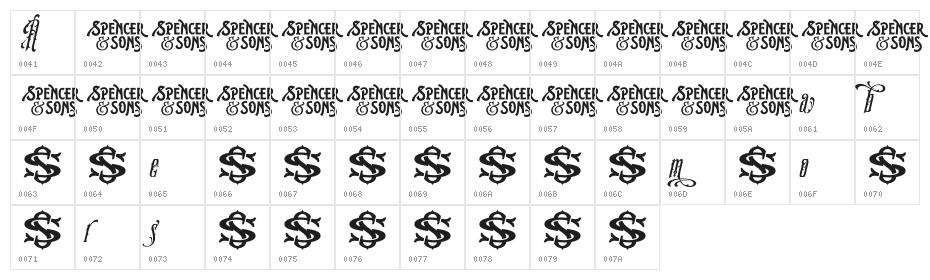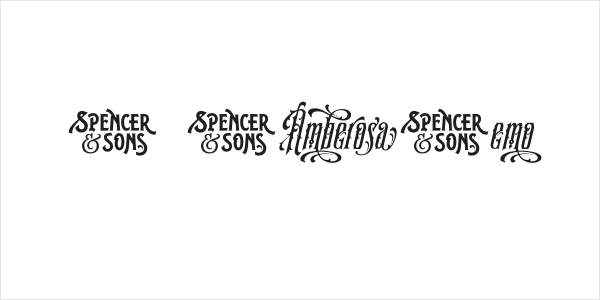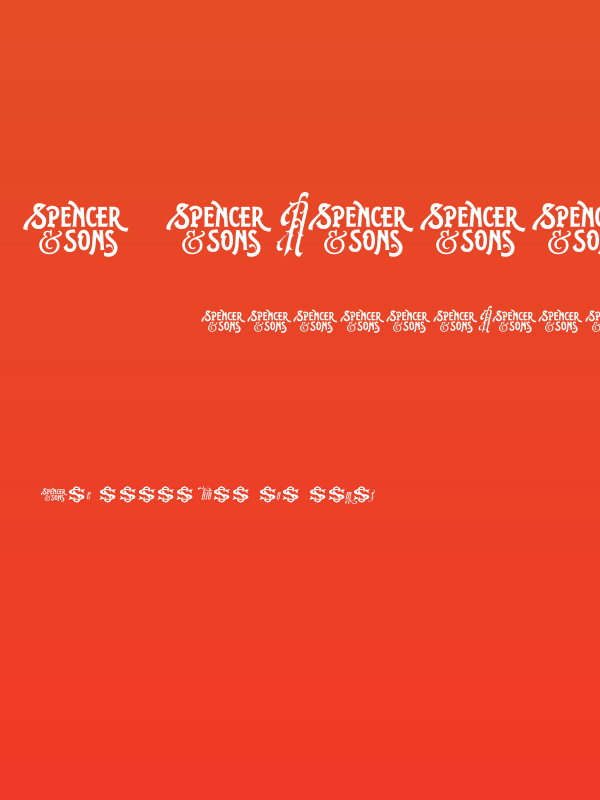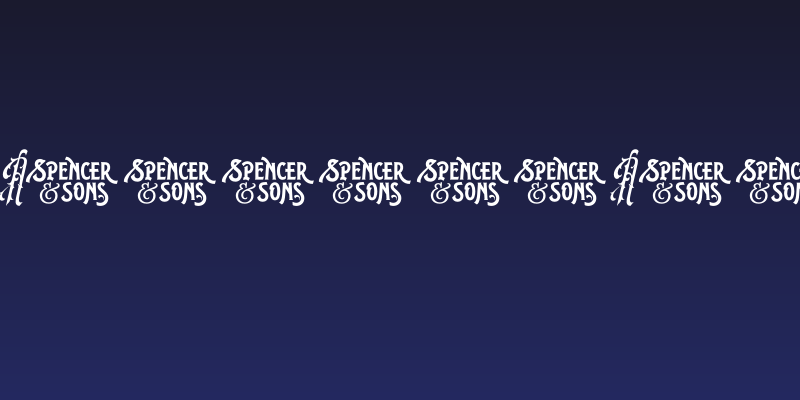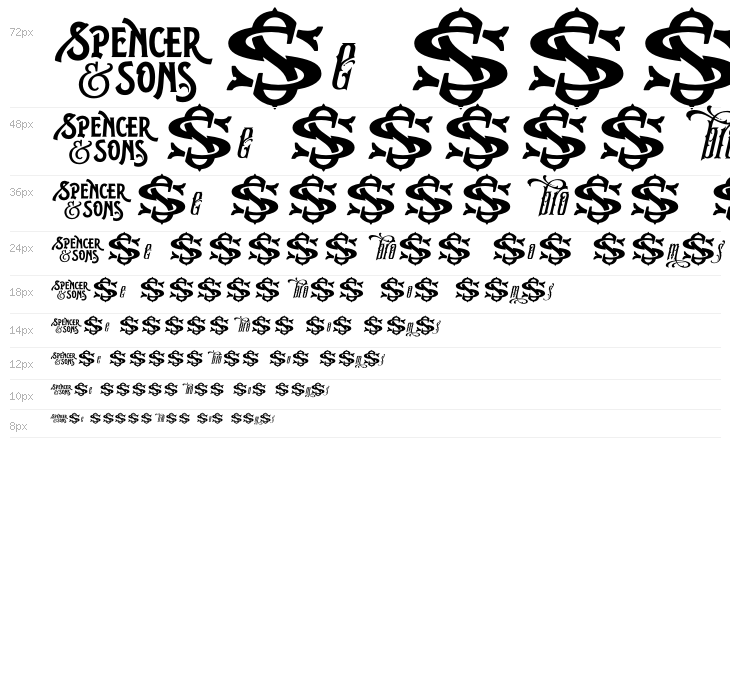
S&SAmberosaDemo Font
✎ Calligraphic
| Kategorien | Calligraphic |
| Gesamtstil | Vintage |
| Anwendungsfall | Logos, Headlines, Invitations |
| Vorgeschlagene Projekte | Ideal for branding, logos, invitations, and decorative headlines. |